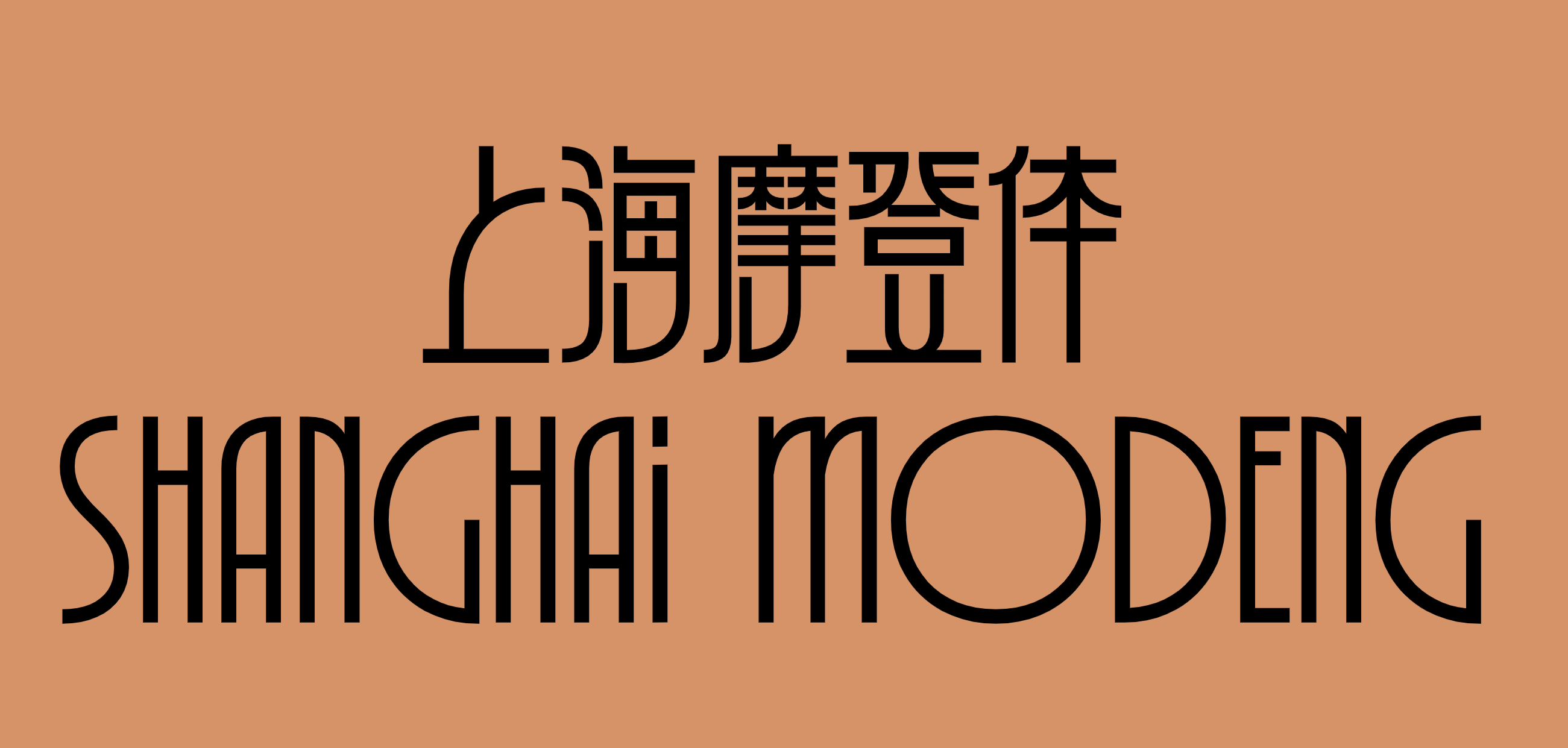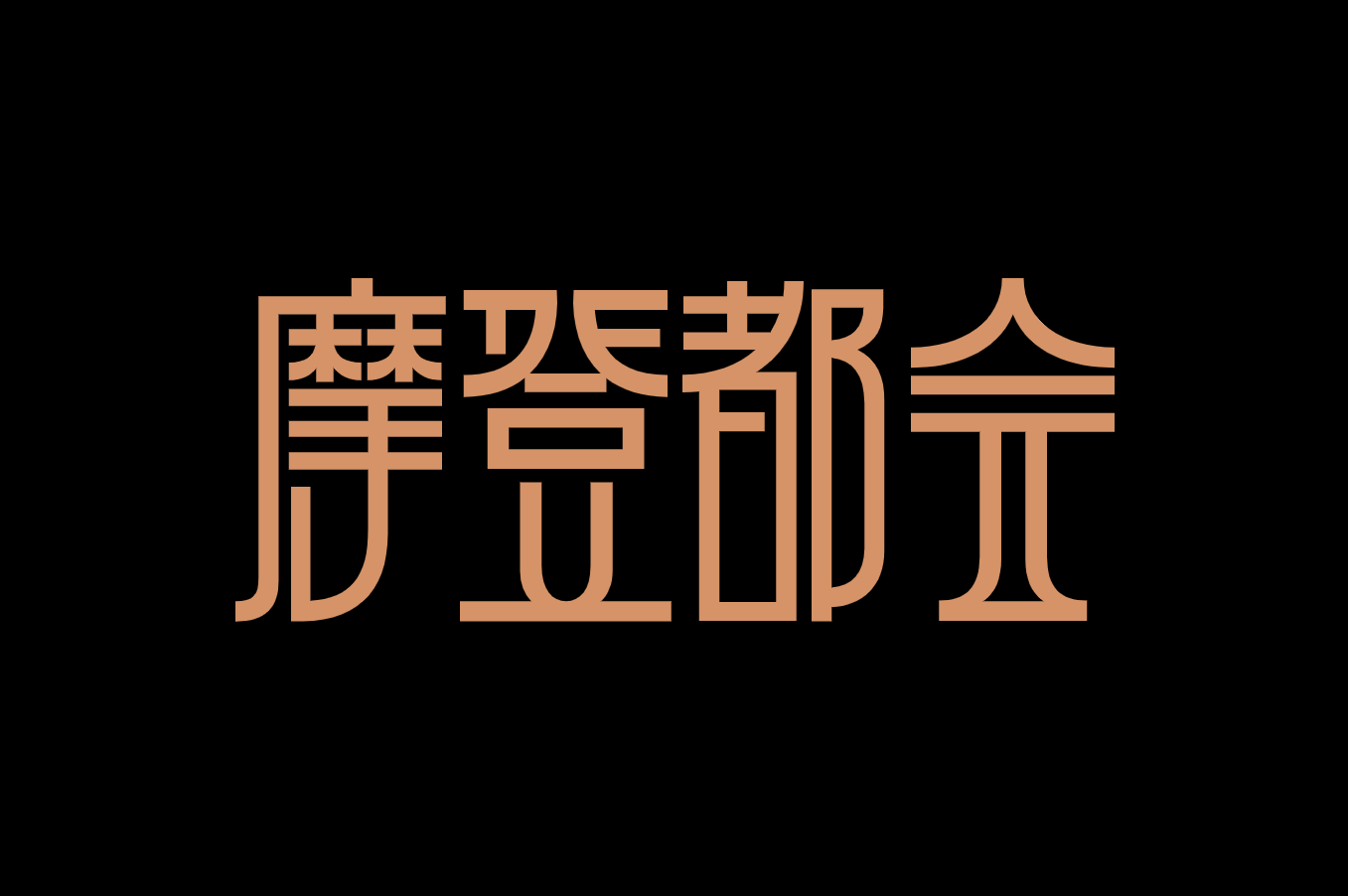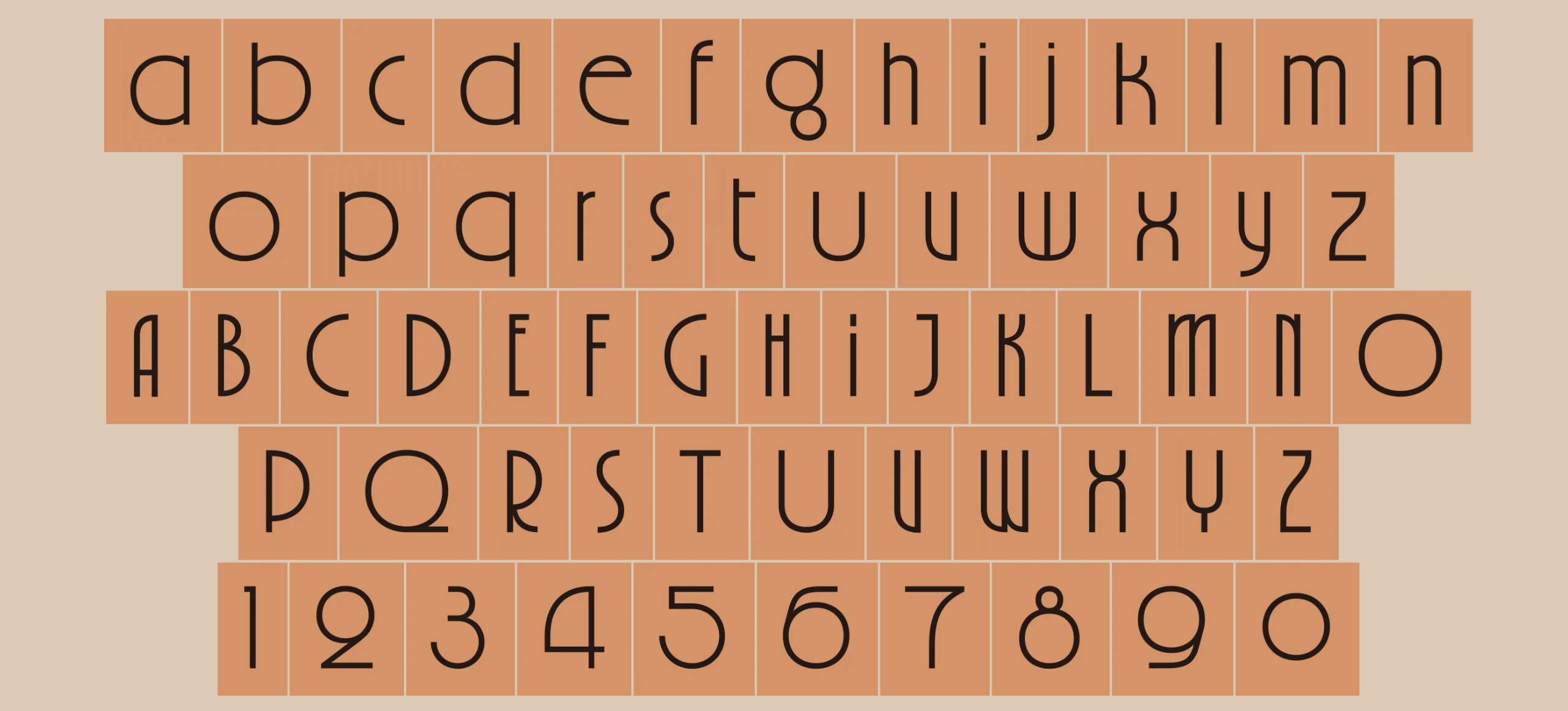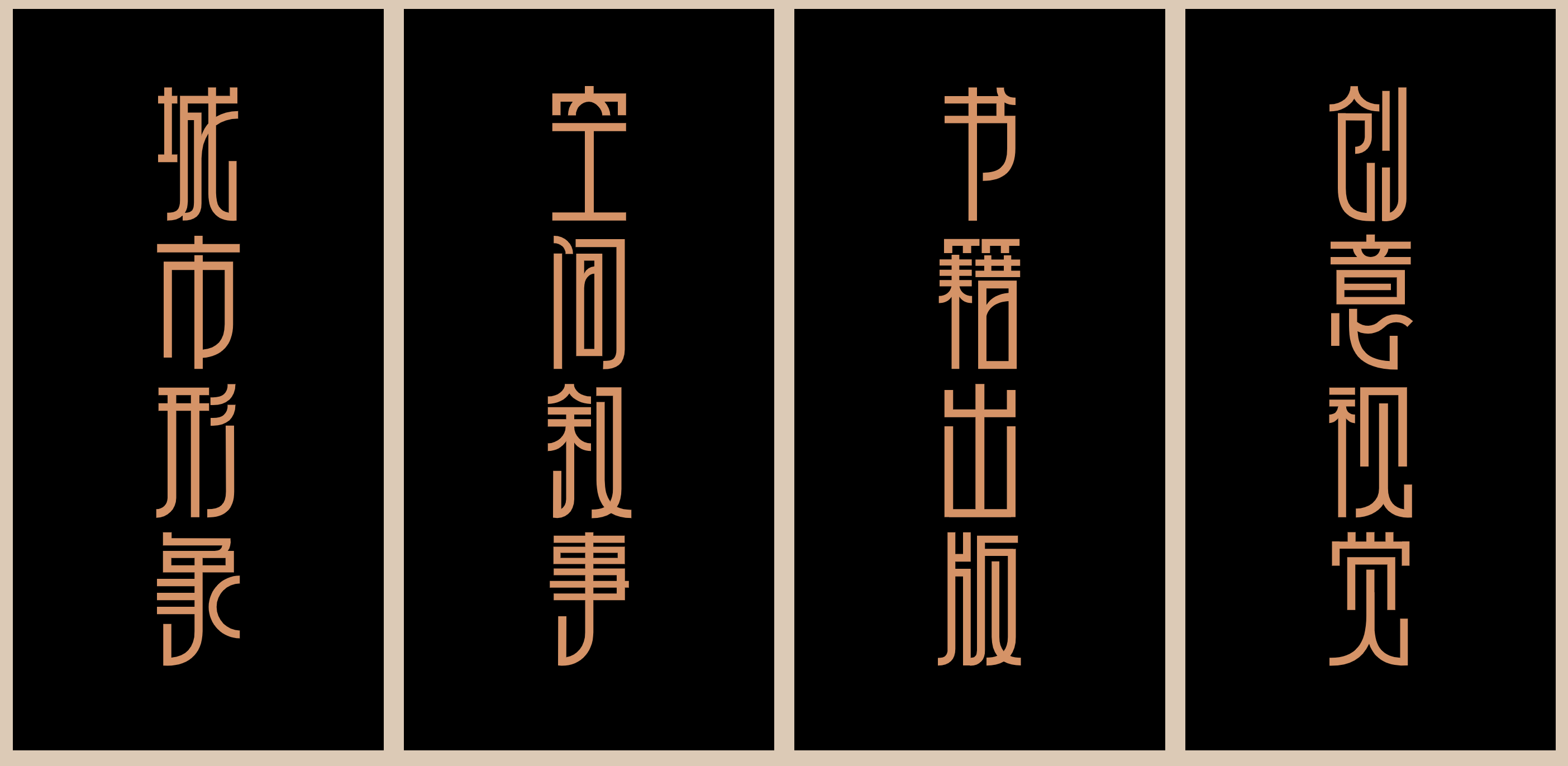
9月23日,“上海摩登体”(Shanghai Modeng)正式发布。这是国内首款以城市文化为主题的中西文字体,其灵感源于装饰艺术风格。字库共收录7293个字符,目前已向社会开源共享。公众可通过“上海摩登体”
上海摩登体(Shanghai Modeng)是中国首个以城市文化为源流的中西文字体。字库按照GB2312国标标准研发。这款字体溯源了1930至40年代伴随着上海都市文化的起源与涌现,影响与遍及了各种视觉文化形态的装饰艺术(Art Déco)运动。这款字体的设计不是对装饰艺术风格的形式复刻,而是在秉承装饰艺术运动融合多元文化与创新未来的时代精神的同时,通过独特的字形语言,向城市文明演进的过去、现在与未来的提问。
上海摩登体的西文字体既严格遵循与中文字体统一的设计逻辑,同时深入考量西文排版的语境特征,巧妙地在西文字体的传统与创新之间实现平衡。小写字母采用了较高的x高度,特意强调了字母的圆弧造型,与其他字身较窄的字母形成鲜明的对比,塑造出富有几何韵律的视觉张力。另外,西文字体通过OpenType字体技术,增加了西文字符的连笔功能,使得字符之间的组合灵活多变、自然流畅。
上海摩登体的阿拉伯数字采用富有弹性和力度的圆弧形线条,字形精致饱满,趣味生动。标点符号的设计延续了中文字形修长的视觉特征,重心上移,冒号、分号打破常规布局,从细微之处增强了上海摩登体的独特气质。
作为一款融合当代城市文化精神的创新字体,上海摩登体在历史传承与未来创新之间建立了对话。其富有表现力的现代几何造型,不仅能为品牌、广告、包装、游戏和出版物提供鲜明的视觉形象,还能在城市形象、空间叙事和文旅体验中展现其独特的风格与魅力。